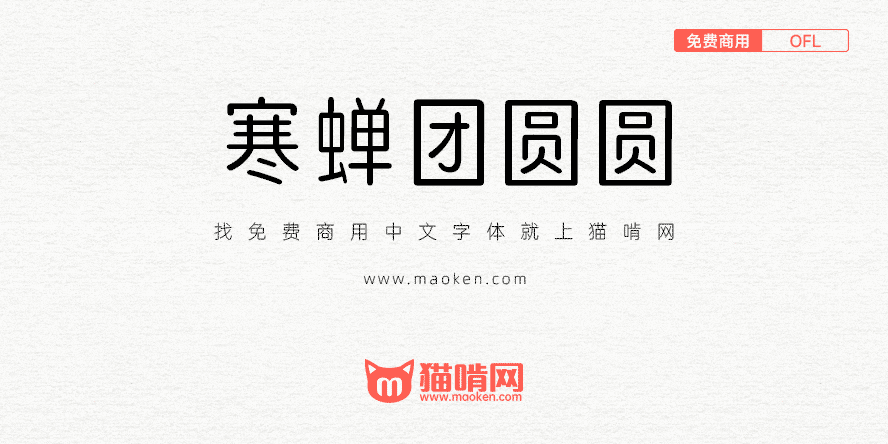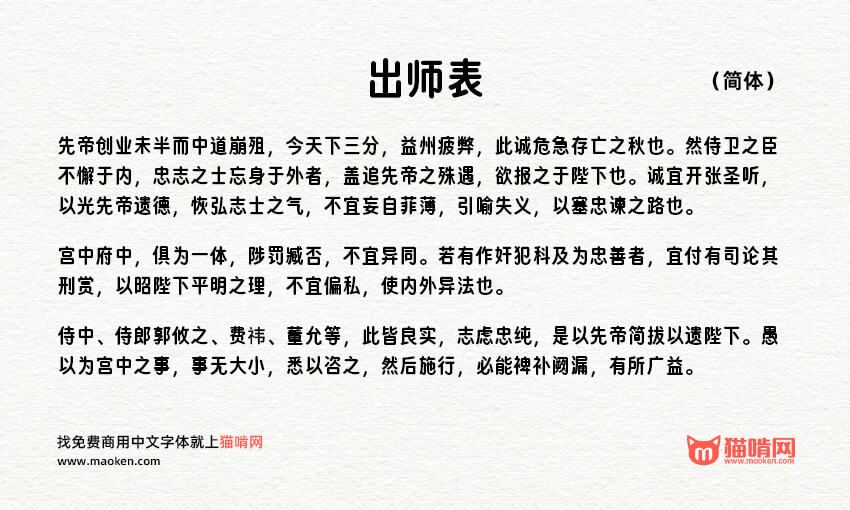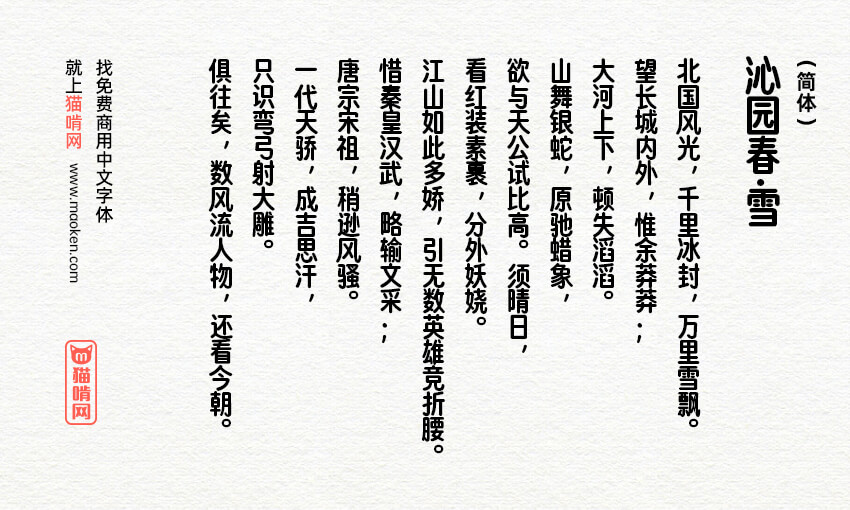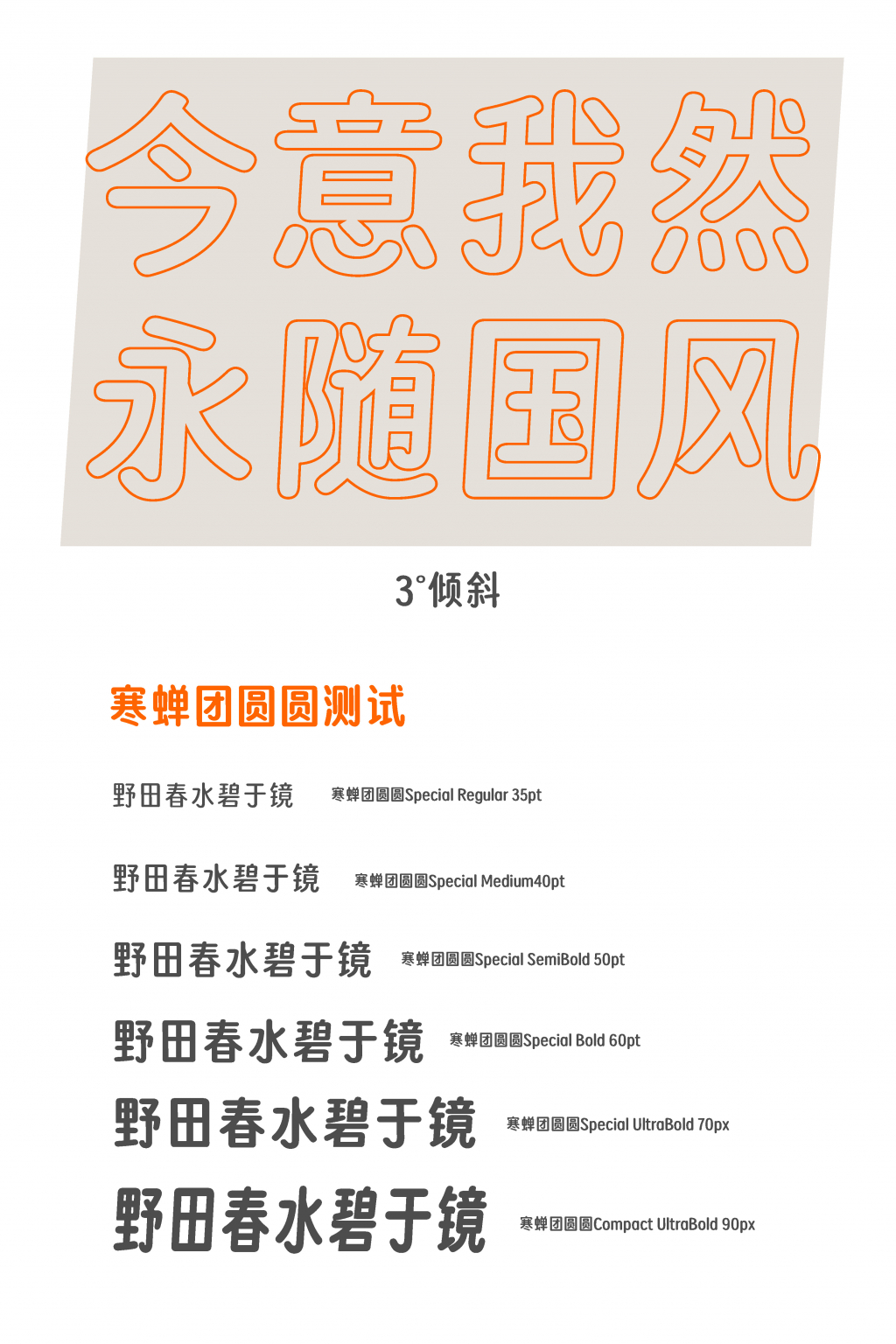
寒蝉团圆体:继承得意黑二创柔和圆角风格字体 开源免费商用
字体作者:萧熠Siue (中国大陆) 字体字重:1个
得意黑二创字体。 具有倾斜趋势,修改倾斜角度为3°。 新增若干字符,优化竖排特性。
感觉这个字体35和55字重的字形有的笔画细得有些不自然
这个粗体看着笔画粘连比较少,是程序算法调整的还是手动调整的?